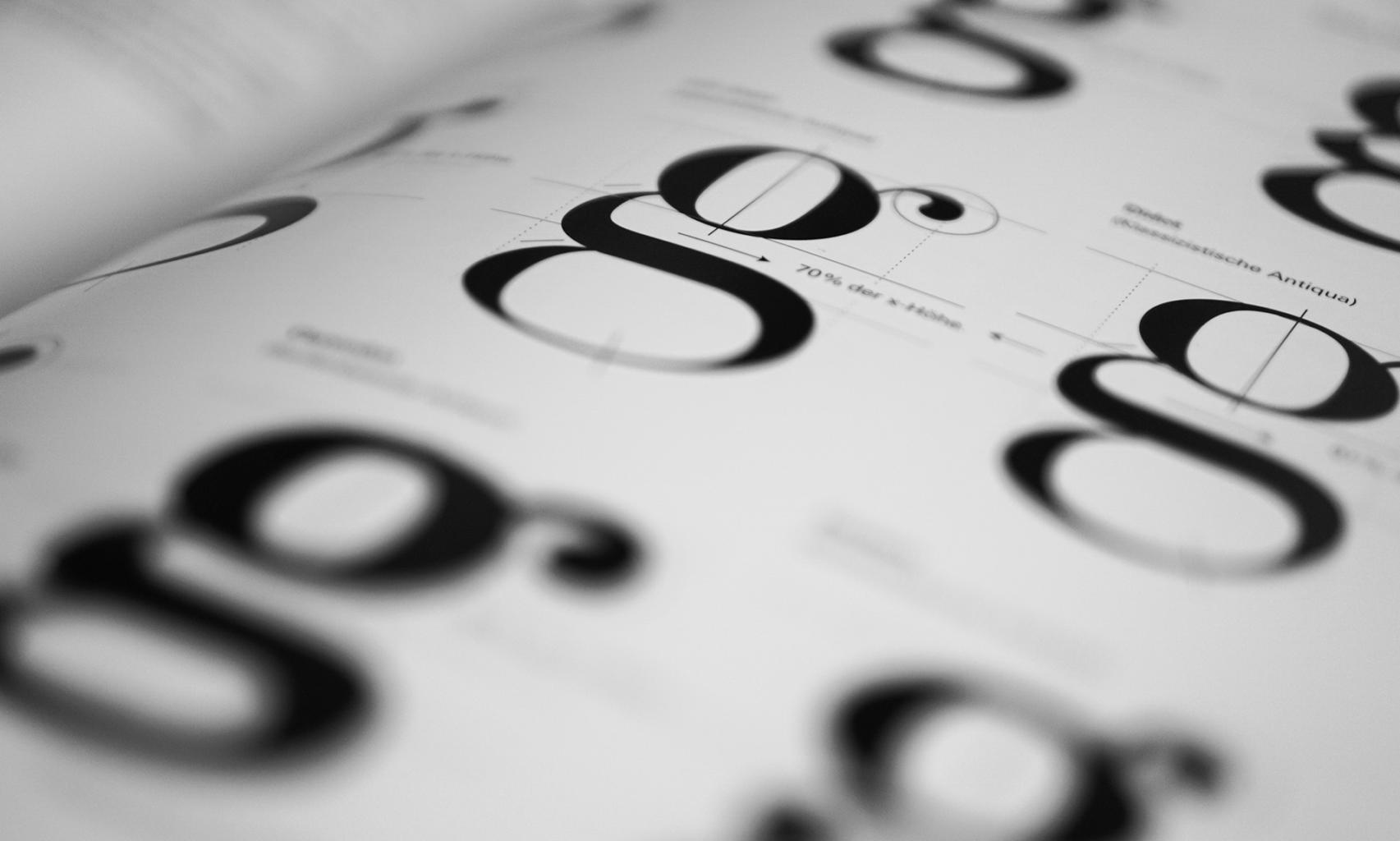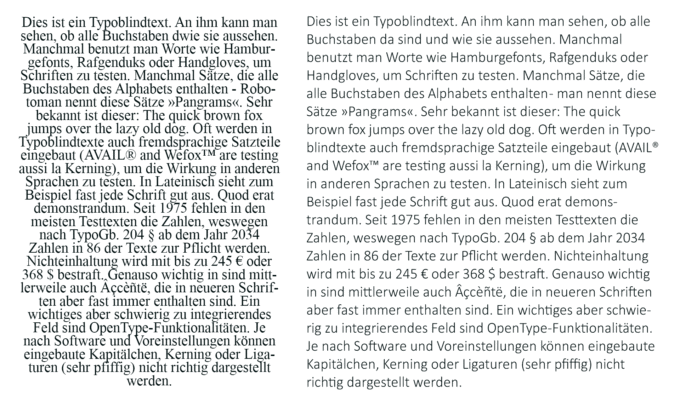
„Wir nehmen wahr, bevor wir verstehen. Typografie funktioniert wie Hintergrundmusik: Man hört nicht hin, unbewusst macht sie aber doch Stimmung“, erklärt der Typografie- und Design-Experte Erik Spiekermann in einem Interview mit dem Digital-Business-Magazin t3n. Ob beim Logo-Design für die eigene Marke, der Entwicklung der nächsten Plakat-Kampagne oder der Gestaltung einer neuen Landingpage – hinsichtlich der Schriftwirkung gibt es bei der Schriftwahl einiges zu beachten.
Anforderungen bei der Wahl von Web- und Printschriften
Grundsätzlich unterscheiden wir zwischen Web- und Printschriften. Die beiden Anwendungsbereiche stellen viele gemeinsame, jedoch auch viele unterschiedliche Anforderungen, die es bei der Wahl der passenden Schriftart zu beachten gibt. Im Gegensatz zum Printbereich gibt es im Web wesentlich weniger Schriftarten, sogenannte Webfonts, die zur Auswahl stehen. Denn aufgrund der Umwandlung von Kurven in eckige Pixel können nicht alle Schriftarten im digitalen Bereich verwendet werden. Vor der Entscheidung für einen Webfont sind deshalb umfassende Tests nötig. Responsivität ist ebenfalls ein großes Thema. Dabei geht es nicht nur um die allgemeine Responsivität einer Webseite, sondern zunehmend auch um die befüllenden Details wie responsive Schriften. Sogenannte Variable Fonts sollen die Vision von stufenlos anpassbaren Schriften und damit den Wunsch nach qualitativ hochwertiger Typografie im Web erreichbar machen. Die Variable Fonts erlauben es die Strichstärken, Kontraste, Breiten, Serifenlängen und viel weitere Einstellungen stufenlos zu verändern, sodass dieselbe Schrift auf unterschiedlichen Endgeräten oder für unterschiedliche Zielgruppen optimiert werden kann.
Was beeinflusst die Lesbarkeit von Schriften?
Was nutzt die schönste Schrift, wenn man sie nicht lesen kann? Als oberstes Gebot gilt sowohl im Web als auch auf Printprodukten die gute Lesbarkeit von Schriften. Als routinierte Leser erfassen wir nicht jeden Buchstaben einzeln, sondern bestimmte Buchstabengruppen zusammen. Trotzdem „fährt“ das Auge jede einzelne Zeile entlang. Damit ein Textabschnitt gut lesbar ist, müssen sich die Zeilen deshalb einfach verfolgen lassen und gut voneinander zu unterscheiden sein – genau wie die einzelnen Buchstaben untereinander. Außerdem muss sich der neue Zeilenanfang schnell und einfach finden lassen.
Beispiel für weniger gut lesbaren Text (links) und gut lesbaren Text (rechts):
Für die Erstellung eines gut lesbaren Textes gibt es einige beeinflussende Faktoren und Faustregeln:
Serifen vs. Groteske
Die Meinung, dass gerade bei großen Textmengen Serifen zu einer besseren Lesbarkeit beitragen, ist weit verbreitet. Die Serifen bilden auf der Schriftlinie eine optische Führung, verhindern, dass der Leser in der Zeile verrutscht, und können dadurch häufig mit einem geringeren Zeilenabstand gesetzt werden. Serifen-Schriften sind im Printbereich – vor allem in Zeitungen oder Büchern –weit verbreitet. Am Bildschirm stellen Serifen-Schriften häufig ein Problem dar, denn sie werden aufgrund der geringeren Auflösung und des eckigen Monitorrasters nicht optimal dargestellt. Erst ab einer Schriftgröße von 16 pt leidet die Schriftwirkung von Serifenfonts am Bildschirm nicht mehr. Im Web werden deshalb überwiegend Groteske, also serifenlose Schriften bzw. Sans Serifs eingesetzt.
Aber auch innerhalb der zwei Gruppierungen gibt es Unterschiede. Einige Grotesk-Schriften (z. B. Futura Std Book) beruhen auf geometrischen Formen. Die Spiegelungen und durchgängig sehr ähnlichen Strichstärken verleihen den Schriften eine ausdrucksstarke Wirkung, beeinträchtigen aber den Lesefluss, da es leicht zu Verwechslungen zwischen den Buchstaben kommen kann. Sogenannte humanistische serifenlose Schriften (z. b. Arial) sind dynamischer und lassen sich besser lesen.
Schriftgröße
Größer bedeutet nicht gleich besser. Ausschlaggebend für die Wahl der Schriftgröße sind Lesedistanz und Zielgruppe. Zum Beispiel werden Plakate und Banner in der Regel aus einer größeren Distanz betrachtet als Flyer oder Postkarten. Für ältere oder hinsichtlich des Sehens beeinträchtigte Personen darf die Schriftgröße bzw. der Schriftgrad nicht zu klein sein. Zu beachten ist, dass verschiedene Schriftarten in ein und derselben Schriftgröße aufgrund ihrer unterschiedlichen Proportionen unterschiedlich groß wirken können. Die Schriftgrößen lassen sich in drei Kategorien einteilen:
- Konsultationsgröße: Schriftgröße bis 8 pt. Sie ist für Texte vorgesehen, die nur kurz konsultiert werden. Diese weniger umfangreichen Texte können zum Beispiel Fußnoten, Randbemerkungen oder Bildunterschriften sein.
- Lesegröße: Eine angenehme Lesegröße liegt im Printbereich zwischen 9 und 12 pt. Im Web sollte der Schriftgrad zwischen 10 und 14 Pixeln liegen (hier finden Pixel statt Punkt Anwendung). Diese Schriftgrößen sind für größere Textmengen gedacht, für die mehr Zeit zum Lesen nötig ist und welche dadurch das Auge stärker und länger beanspruchen. Beispiele aus dem Printbereich sind Zeitungs- und Zeitschriftenartikel, Bücher oder Broschüren.
- Schaugröße: Im Printbereich spricht man ab Schriftgröße 14 pt und im Web ab 15 Pixel von einer sinnvollen Schaugröße. Der entsprechende Textteil soll auffallen und die Aufmerksamkeit des Lesers auf sich lenken. Die Schaugröße eignet sich für Überschriften, Slogans oder Buchtitel.
Zeilenlänge
Sowohl zu lange als auch zu kurze Zeilen behindern den Lesefluss. Als Orientierung gilt: Bei Printprodukten sollte eine Zeile nicht weniger als 35 bis 40 Zeichen haben. Ideal sind 60 bis 70 Zeichen pro Zeile. Im Web gelten 50 bis 80 Zeichen als ideal. Je schmaler die verwendete Schriftart ist, desto kürzer wird dementsprechend die Zeile ¬– und umgekehrt. Außerdem gilt in Bezug auf die Lesbarkeit und Schriftwirkung: Je länger die Zeile, desto größer sollte der Abstand zwischen den einzelnen Zeilen sein.
Zu beachten ist der Unterschied zwischen «Lesbarkeit» und «Leserlichkeit»: Für die Lesbarkeit ist der Textverfasser zuständig (Verständlichkeit eines Textes), für die Leserlichkeit der Typograf (Schriftbild, Gestaltung). Korrekterweise müssten in obenstehendem Artikel die meisten Begriffe «lesbar» durch «leserlich» ersetzt werden.